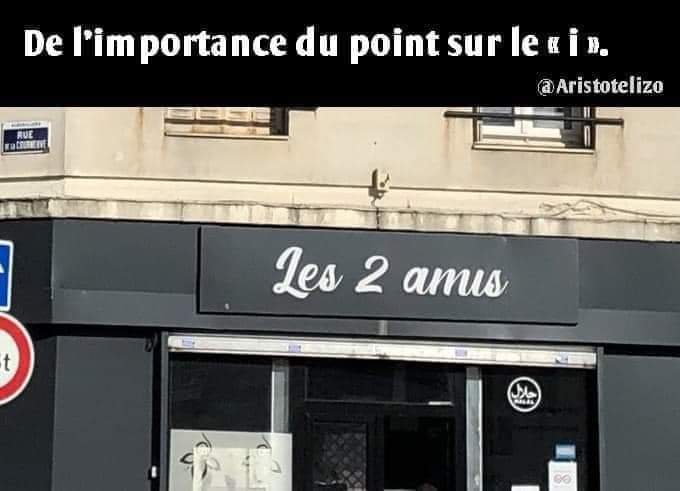
Un ami vient de m'envoyer ça. Cette image a peut-être déjà bien
circulé, je l'ignore. Je ne la connaissais pas. Elle prouve que
les accents sur les capitales ne sont pas les seuls à provoquer
des confusions... l'absence des points sur les i bdc aussi,
parfois. Je glisse sur le 2 qu'il aurait été préférable de mettre
en toutes lettres.